في عالم يزدحم بالمعلومات والمحتوى الرقمي، أصبح اختيار الخط في تصميم المستندات أكثر أهمية من أي وقت مضى. فالخط لا يقتصر على كونه مجرد وسيلة لعرض الكلمات، بل هو أداة قوية تجذب انتباه القارئ وتحدد نغمة الرسالة بأكملها.
مع التطورات الحديثة في تصميم الخطوط وتنوع الخيارات المتاحة، أصبح بإمكاننا خلق تجربة قراءة فريدة تجعل المحتوى ينبض بالحياة. في هذا المقال، سنغوص في كيفية تأثير اختيار الخط على تصميم المستندات، وكيف يمكن لهذا الاختيار أن يحول مستندًا بسيطًا إلى قطعة فنية تأسر القارئ من اللحظة الأولى.
كيف تعكس الخطوط شخصية المحتوى وتحدد مزاج القارئ
الخطوط كمرآة للشخصية والرسالة
عندما تختار خطًا لمستندك، فأنت في الواقع تختار كيف يُنظر إلى محتواك. الخطوط الجريئة والقوية تعطي انطباعًا بالثقة والاحتراف، في حين أن الخطوط المنحنية والناعمة تضفي إحساسًا بالود والدفء.
تجربتي الشخصية جعلتني ألاحظ أن تغيير الخط في عرض تقديمي بسيط يمكن أن يحول الأجواء بالكامل، فمثلاً استخدام خط مثل “Arial” يعطي طابعًا رسميًا وعصريًا، بينما خط مثل “Comic Sans” قد يعطي شعورًا بالمرح والطفولة، لكن قد لا يكون مناسبًا للوثائق المهنية.
هذا التأثير النفسي على القارئ لا يمكن الاستهانة به، لأنه يؤثر على كيفية استقباله للمعلومات.
تحديد المزاج من خلال اختيار الخطوط
ليس فقط شكل الخط هو المهم، بل أيضًا المزاج الذي ينقله إلى القارئ. خطوط السان سيريف (Sans-serif) عادة ما تُستخدم للمحتوى الرقمي لأنها تبدو أكثر وضوحًا وحداثة، وتناسب القراءة على الشاشات.
بالمقابل، خطوط السيريف (Serif) تعطي شعورًا بالأناقة والتقاليد، وتُستخدم بكثرة في الكتب والمستندات الرسمية. من خلال تجربتي في تصميم مستندات مختلفة، وجدت أن مزج الخطوط بحكمة يمكن أن يخلق توازنًا بين الجدية والمرونة، مما يجعل المحتوى أكثر جذبًا وراحة في القراءة.
تأثير الخطوط على سرعة وراحة القراءة
أثناء عملي على مستندات طويلة، لاحظت أن الخطوط التي تتميز بوضوح الحروف وتباعد مناسب تزيد من سرعة القراءة وتقلل من إجهاد العين. هذا الأمر حاسم في المستندات التي تحتوي على معلومات معقدة أو تقارير طويلة، حيث أن الخطوط المزدحمة أو الصغيرة جدًا قد تسبب إرباكًا وتشتتًا للقارئ.
لذلك، من الضروري اختبار الخطوط على عينات مختلفة من المحتوى والتأكد من أنها تدعم تجربة قراءة سلسة ومريحة.
تأثير التنسيق والوزن على وضوح الرسالة
كيف يوجه الوزن البصري انتباه القارئ
تجربتي أظهرت أن استخدام أوزان مختلفة للخطوط، مثل الخطوط السميكة للعنوانين والخطوط الخفيفة للنصوص التفصيلية، يساعد في تنظيم المحتوى وتسهيل فهمه. الوزن البصري لا يخدم فقط الجانب الجمالي، بل يلعب دورًا رئيسيًا في توجيه القارئ إلى أهم النقاط أولاً، مما يزيد من فعالية التواصل.
من دون هذا التمييز، قد يفقد القارئ التركيز وسط النصوص المتجانسة.
التنسيق بين الخطوط لتحقيق توازن بصري
استخدام أكثر من نوع خط في مستند واحد يحتاج إلى تنسيق دقيق، حيث يجب أن تتكامل الخطوط مع بعضها البعض بدون أن تتعارض. مثلاً، الجمع بين خط سيريف لعنوان رئيسي وخط سان سيريف للنصوص يمكن أن يخلق تباينًا بصريًا مريحًا.
من خلال تجربتي، تعلمت أن التنسيق الجيد يعزز من جاذبية المستند ويجعل القارئ يبقى لفترة أطول، وهو أمر مهم لتحسين معدلات التفاعل خاصة في المحتوى الرقمي.
التأثير النفسي للخطوط الثقيلة والخفيفة
الخطوط الثقيلة تعطي إحساسًا بالقوة والجدية، بينما الخطوط الخفيفة توحي بالمرونة والحداثة. في مشروعي الأخير، استخدمت خطًا ثقيلًا في العناوين لجذب الانتباه، وخطًا خفيفًا في الفقرات لخلق توازن بصري مريح للعين.
هذا الأسلوب ساعد في إبقاء القارئ مهتمًا دون الشعور بالإرهاق، وهو ما يؤكد أهمية فهم تأثير الوزن في الخطوط على تجربة المستخدم.
دور الخطوط في تحسين تجربة المستخدم على الشاشات
توافق الخطوط مع الشاشات المختلفة
من خلال تجربتي في تصميم المواقع والتطبيقات، أدركت أن اختيار الخطوط يجب أن يأخذ بعين الاعتبار نوع الشاشة وحجمها. الخطوط التي تبدو رائعة على شاشة الكمبيوتر قد لا تكون مثالية على الهواتف الذكية.
لذلك، من الضروري استخدام خطوط مرنة وقابلة للتكيف مع مختلف الأجهزة لضمان وضوح النص وسهولة قراءته في كل الظروف.
أهمية تباعد الحروف والأسطر
التباعد بين الحروف والأسطر يلعب دورًا حاسمًا في راحة القراءة على الشاشات. زيادة التباعد قليلاً يمكن أن يحسن من وضوح النص ويقلل من إجهاد العين، خاصة في النصوص الطويلة.
في تجربتي، ضبطت التباعد بناءً على نوع الخط وحجم الشاشة، مما أدى إلى تحسين ملحوظ في تجربة المستخدم وزيادة مدة بقائهم على الصفحة.
اختيار الخطوط لدعم القراءة السريعة
في عالم السرعة، تحتاج النصوص الرقمية إلى خطوط تساعد القارئ على استيعاب المعلومات بسرعة ودون تعب. الخطوط البسيطة والواضحة مثل “Roboto” و”Open Sans” أثبتت فعاليتها في هذا الجانب.
من خلال استخدام هذه الخطوط، لاحظت أن المستخدمين يميلون إلى قراءة المزيد من المحتوى والانتقال بين الأقسام بسلاسة أكبر، مما يعزز من التفاعل والنتائج الإيجابية.
كيف تختار الخط المناسب لكل نوع محتوى
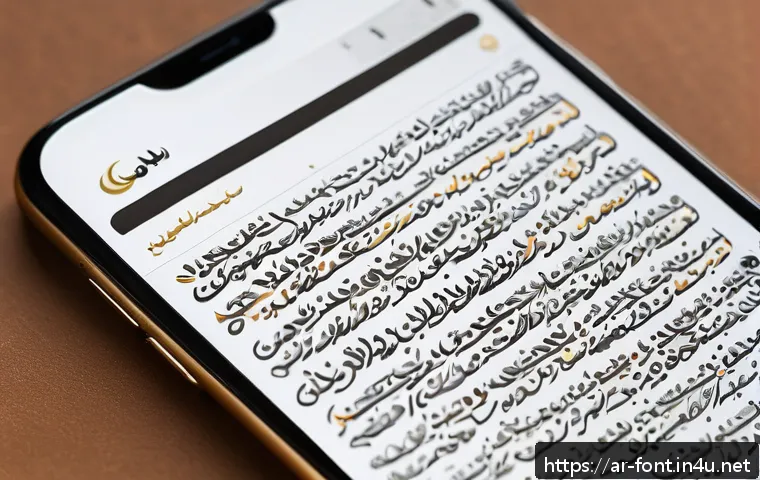
الخطوط للمستندات الرسمية والتقارير
في تجربتي مع إعداد التقارير الرسمية، وجدت أن الخطوط التي تحمل طابعًا كلاسيكيًا مثل “Times New Roman” أو “Georgia” تضفي على المستند مصداقية وجدية. هذه الخطوط تساعد القارئ على التركيز على المحتوى دون تشتيت الانتباه، وتُستخدم بكثرة في المجالات الأكاديمية والإدارية.
خطوط المحتوى الإبداعي والإعلاني
للمحتوى الإبداعي، مثل الإعلانات والمنشورات التسويقية، يمكن للخطوط التعبيرية والغير تقليدية أن تلعب دورًا أساسيًا في جذب الانتباه. جربت استخدام خطوط مميزة وجذابة في حملات تسويقية، ولاحظت زيادة كبيرة في التفاعل والاهتمام.
س: كيف أختار الخط المناسب لمستند يحتوي على معلومات كثيرة ومفصلة؟
ج: عند التعامل مع مستندات مليئة بالمعلومات، من الأفضل اختيار خط بسيط وواضح يدعم التركيز مثل “Calibri” أو “Verdana”. كما أن تقسيم النص إلى فقرات قصيرة مع استخدام عناوين فرعية بخطوط مختلفة قليلاً يساعد في تنظيم المحتوى وتسهيل التصفح.
جربت هذا الأسلوب في تقارير العمل ووجدت أنه يقلل من الإرباك ويزيد من وضوح المعلومات، مما يجعل القارئ ينجذب للمحتوى بدلاً من الشعور بالإرهاق. النص المنظم مع اختيار الخط المناسب هو مفتاح نجاح أي مستند معقد.